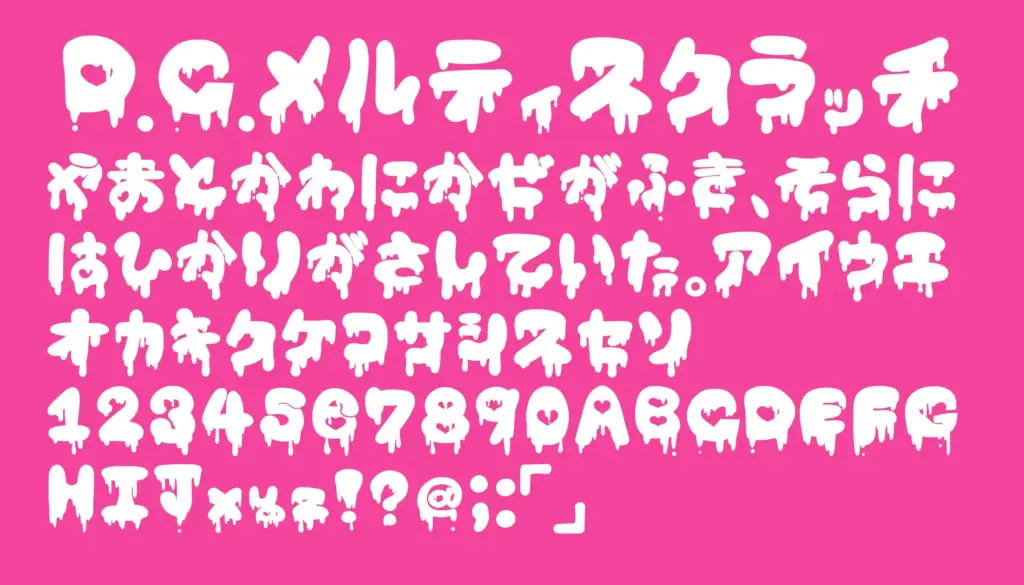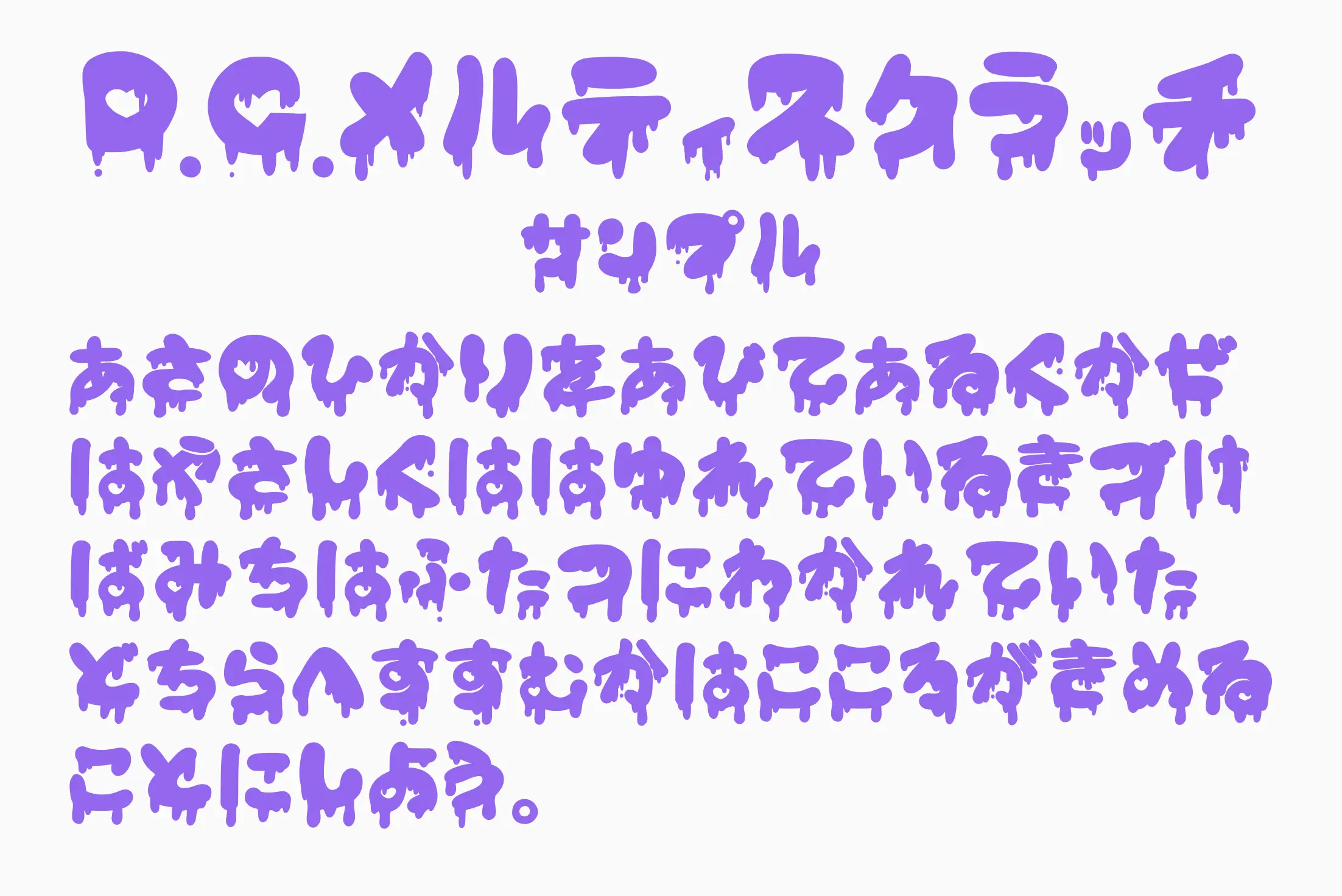
文字がとろけたように崩れる、強い個性が印象的な装飾系フォント。甘さと不穏さが同居する独特のデザインで、見た瞬間に視線を引きつけます。均一すぎない線やシルエットが手作り感を演出し、タイトルやロゴに使うだけで世界観を一気に作り込めるのが魅力。日常的な文章よりも、インパクトを重視したビジュアル表現に向いたフォントです。
D.C.メルティスクラッチ